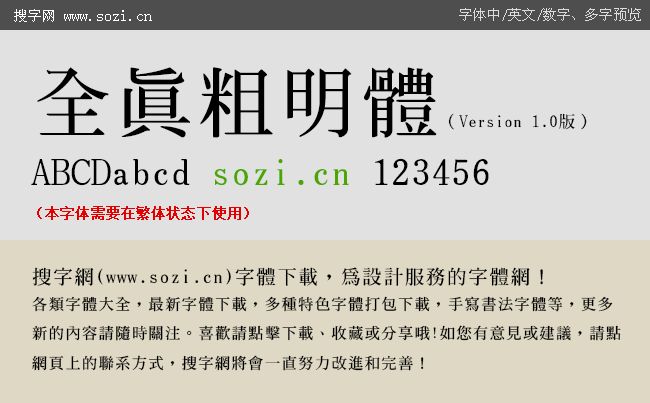
全真粗明體修改正式版
搜字網(wǎng)提供一款全真粗明體修改正式版字體下載,該字體是一款清秀的宋體字體,筆畫(huà)橫輕豎重、結(jié)構(gòu)美觀。字體棱角分明,結(jié)構(gòu)嚴(yán)謹(jǐn),整齊均勻,適用于樣本畫(huà)冊(cè),報(bào)紙排版,網(wǎng)頁(yè)標(biāo)題等廣告設(shè)計(jì)應(yīng)用。